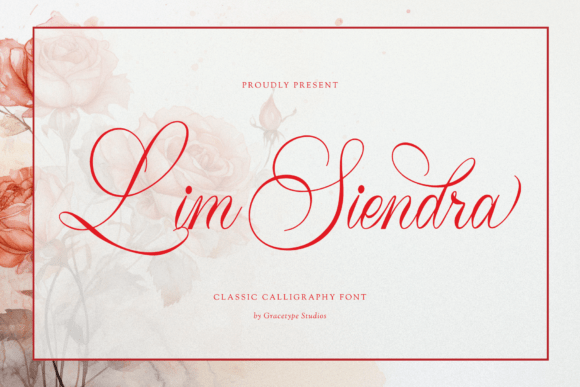
Lim Siendra
Dicipta dengan ketepatan, Lim Siendra menyediakan vektor yang bersih, tipografi yang licin dan lesen komersial untuk ketenangan fikiran.
Sama ada anda mencipta produk POD (Print on Demand), jemputan perkahwinan atau grafik media sosial, Lim Siendra amat bersesuaian.